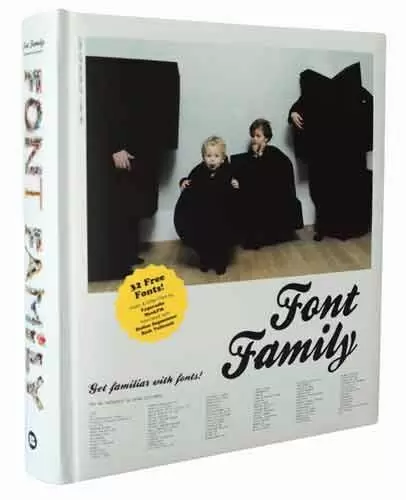
FONT FAMILY
El estudio Julandscape e Index Book vuelven a sorprendernos con su nuevo proyecto: Font Family, un interesantísimo libro que recoge hasta 70 diseñadores y explora las opiniones, actitud y trasfondo de creativos como Rick Valicenti, Stefan Sagmeister y Satoru Nihei.
No se trata de otro pesado y obsoleto análisis de la tipografía y de cómo usarlas correctamente, no, busca la vanguardia, la experimentación, las fuentes más innovadoras y sobre todo las aplicaciones más increíbles con las que deleitar a los posibles lectores/usuarios/consumidores.
Prescindiendo de la simple aplicación académica de la tipografía, indaga en el mundo de la performance y la instalación artística, buscando un nuevo significado, un nuevo horizonte para la tipografía, sin olvidar jamás su funcionabilidad.
356 páginas de auténtico desenfreno tipográfico que harán las delicias de más de uno.
Además, y por si fuera poco, viene acompañado de un CD con 32 fuentes gratuitas, que tal y como está el mercado y con la crisis, nunca están de más.